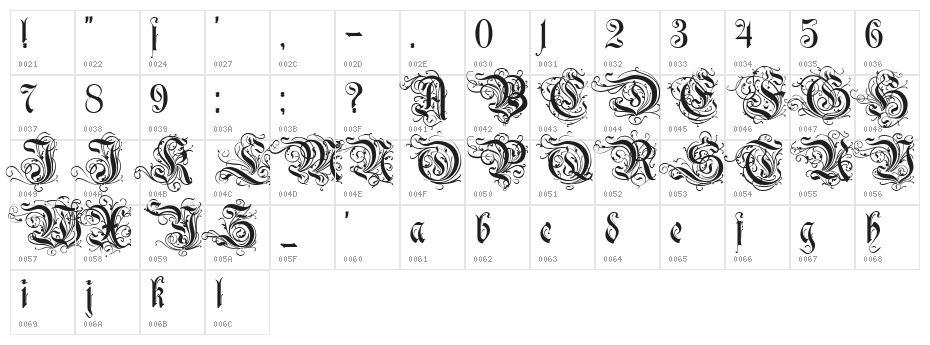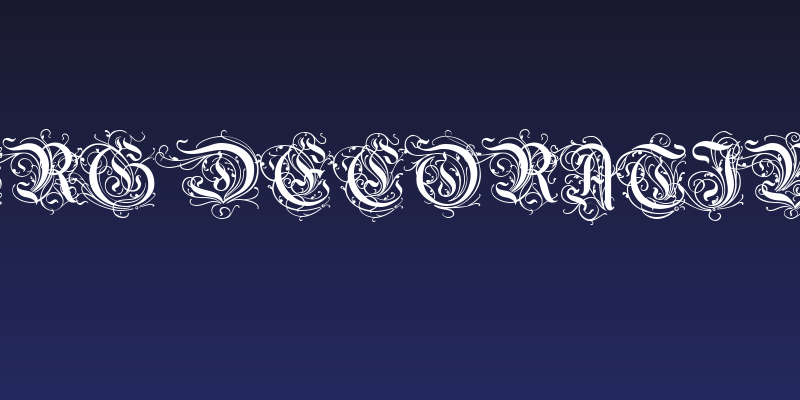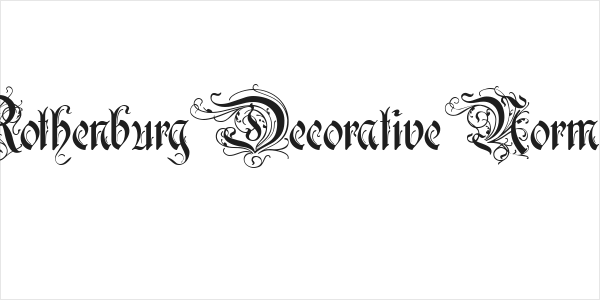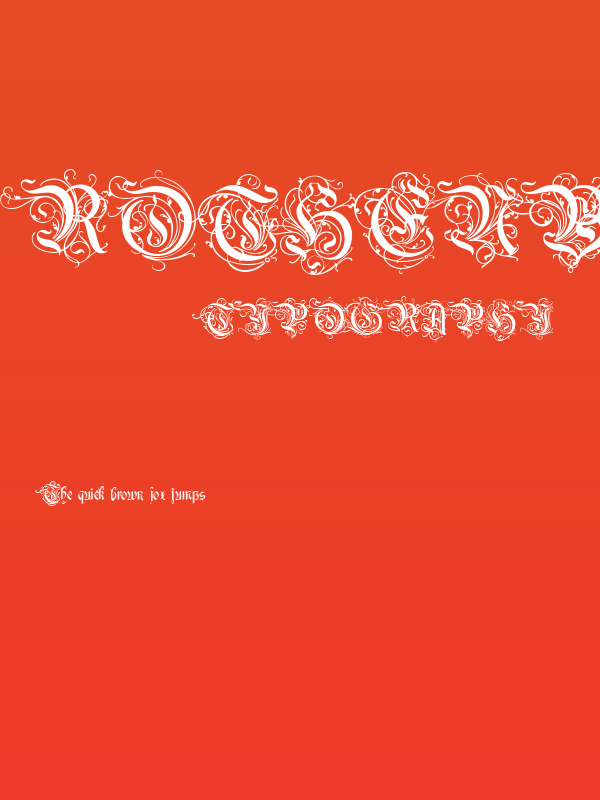
Rothenburg Decorative Normal Font
| حالة الاستخدام | Logos, Headlines |
| مشاريع مقترحة | Ideal for fantasy book covers, historical event invitations, themed posters, and video game graphics. |